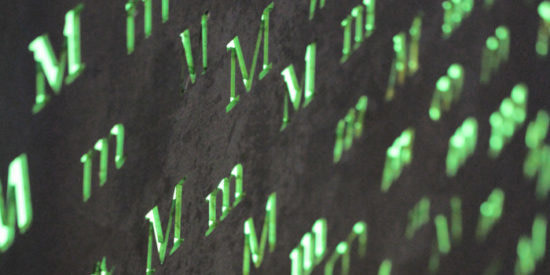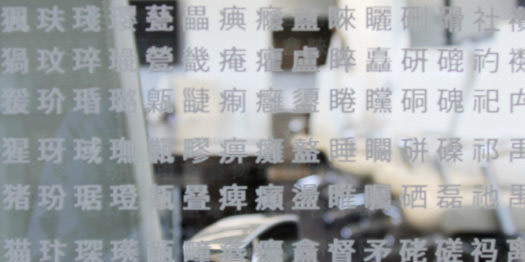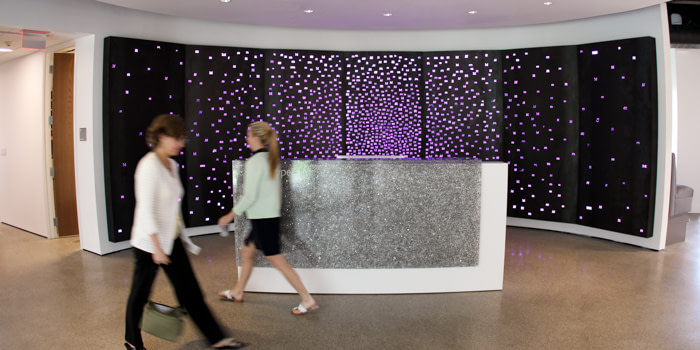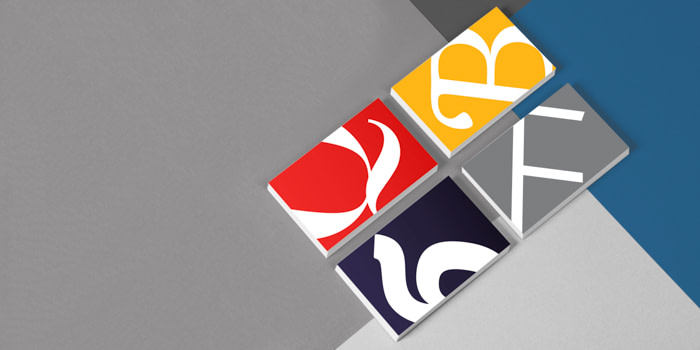
Come Monotype ha rivoluzionato la tipografia nell’era digitale
Scopri come Monotype ha portato la tipografia nel 21° secolo.
Monotype è da oltre un secolo un nome importante nel mondo dell’editoria e del design dei caratteri di stampa. Nel tempo è divenuta un’azienda che fornisce strumenti, tecnologie ed esperienza nel design per contribuire a creare marchi autentici e d’impatto.
Abbiamo parlato con James Fooks-Bale, Direttore Creativo Senior di Monotype, di come si possa comunicare la storia di un’azienda attraverso il marchio e la tipografia.
Dal tradizionale al digitale
Il ricco patrimonio di Monotype è merito della capacità dell’azienda di essere sempre un passo avanti agli altri. “Monotype è nota per la sua capacità di reinventarsi costantemente”, spiega Fooks-Bale. “Per mantenere la nostra posizione, dobbiamo stare al passo con le tendenze del design, i metodi di comunicazione e la tecnologia, in modo da dare ai marchi ciò di cui hanno bisogno prima ancora che se ne rendano conto”.
Le attuali tecnologie dell’azienda riflettono questa filosofia, con un’offerta che include oltre 2.500 famiglie di font, la creazione di font personalizzati e piattaforme che permettono ai marchi di presentare contenuti di marketing visivi. Nel 2016, Monotype ha acquisito Olapic, una piattaforma che consente alle aziende di curare e attivare contenuti dei consumatori, richiederli agli influencer o crearli direttamente. “Questo permette ai marchi di accedere a contenuti che troveranno il favore dei consumatori e di promuovere i propri prodotti in modi più significativi e autentici”, dichiara Fooks-Bale.
Grazie a questa varietà di prodotti, Monotype tiene fede al suo obiettivo di aiutare i clienti a creare esperienze più autentiche con il loro pubblico sotto ogni punto di contatto.
L’elemento chiave del brand
Perché da Monotype prestate così tanta attenzione ai font e al design? “Il carattere è un utile strumento per enfatizzare il marchio”, sostiene Fooks-Bale. “In tanti casi, è più potente degli altri elementi del marchio, come l’illustrazione o il colore, perché spesso è presente anche in altri punti di contatto del marchio”.
Fooks-Bale fa l’esempio di una compagnia aerea. Dai biglietti al fondo delle tazzine da caffè, sono molti i posti in cui si può apporre il logo della compagnia. Per dirla con le parole di Fooks-Bale, “Uno dei pochi ingredienti che è possibile mantenere in ogni situazione è il font.”
“Gli atti visivi e verbali concorrono tutti a creare un marchio autentico e di successo”, spiega Fooks-Bale. “Ma se non sono collegati, non sono efficaci”. Monotype offre ai marchi gli ingredienti per raccontare la propria storia in un modo coerente sotto tutti i punti di contatto. Ciò è essenziale per consentire alle aziende di sviluppare un’identità che esprima in maniera appropriata cosa c’è al centro del loro marchio.
Raccontare storie attraverso i caratteri
I font sono essenziali per comunicare la storia di un marchio, ma Monotype riconosce che ogni font ha una storia a sé; proprio per questo ha creato una serie chiamata Font Stories. Queste storie mettono in risalto alcuni dei suoi design più recenti, suscitando l’interesse dei lettori verso la loro origine. “C’è una storia dietro ogni font, può riguardare il modo in cui ci si è approcciati al design o lo scopo per cui è stato creato”, afferma Fooks-Bale.
Puntando i riflettori sugli ultimi arrivati nella famiglia Monotype, Fooks-Bale spera che il pubblico possa dare una possibilità ai font emergenti. “La nostra offerta è vastissima, il che può sembrare una cosa fantastica”, afferma. “Eppure, se non associamo un racconto ad alcuni font, corriamo il rischio di perdere delle vere gemme”. Attraverso le Font Stories, Monotype getta i semi per aiutare i marchi a valutare il modo in cui alcuni font possono comunicare l’identità di un brand.
Vivere il marchio Monotype
Monotype ha uffici in tutto il mondo, ma è dura essere “un Monotype”. “Vogliamo che i nostri dipendenti vivano e respirino il marchio”, spiega Fooks-Bale. “Il branding non è solo un reparto, ma qualcosa di intrinseco in ognuno di noi”.
Per dare una certa coerenza al marchio, Monotype ha disegnato i suoi Biglietti da Visita in modo tale che rispecchiassero il suo patrimonio tipografico. I biglietti hanno dei frammenti di font Monotype sul retro, il che permette al marchio di mettere in evidenza la sua gamma di design di caratteri. I caratteri sul retro dei biglietti sono aggiornati di frequente, non appena ne vengono presentati di nuovi.
“Per i nostri biglietti utilizziamo il cartoncino Luxe, prodotto da Mohawk, per dar loro più consistenza”, precisa Fooks-Bale. “Distribuire questi biglietti di qualità premium con questa particolare sensazione al tatto fa davvero un’ottima impressione sui clienti con cui lavoriamo di solito”.
Il design è facilmente modificabile e i dipendenti Monotype possono accedervi dal proprio ufficio in qualsiasi parte del mondo attraverso la piattaforma MOO Business Services. “Avevamo bisogno di qualcosa che fosse facile e veloce da produrre”, afferma Fooks-Bale. “Il fatto di avere qualcosa che si potesse ordinare da tutti i nostri uffici nel mondo è stato davvero utile”.